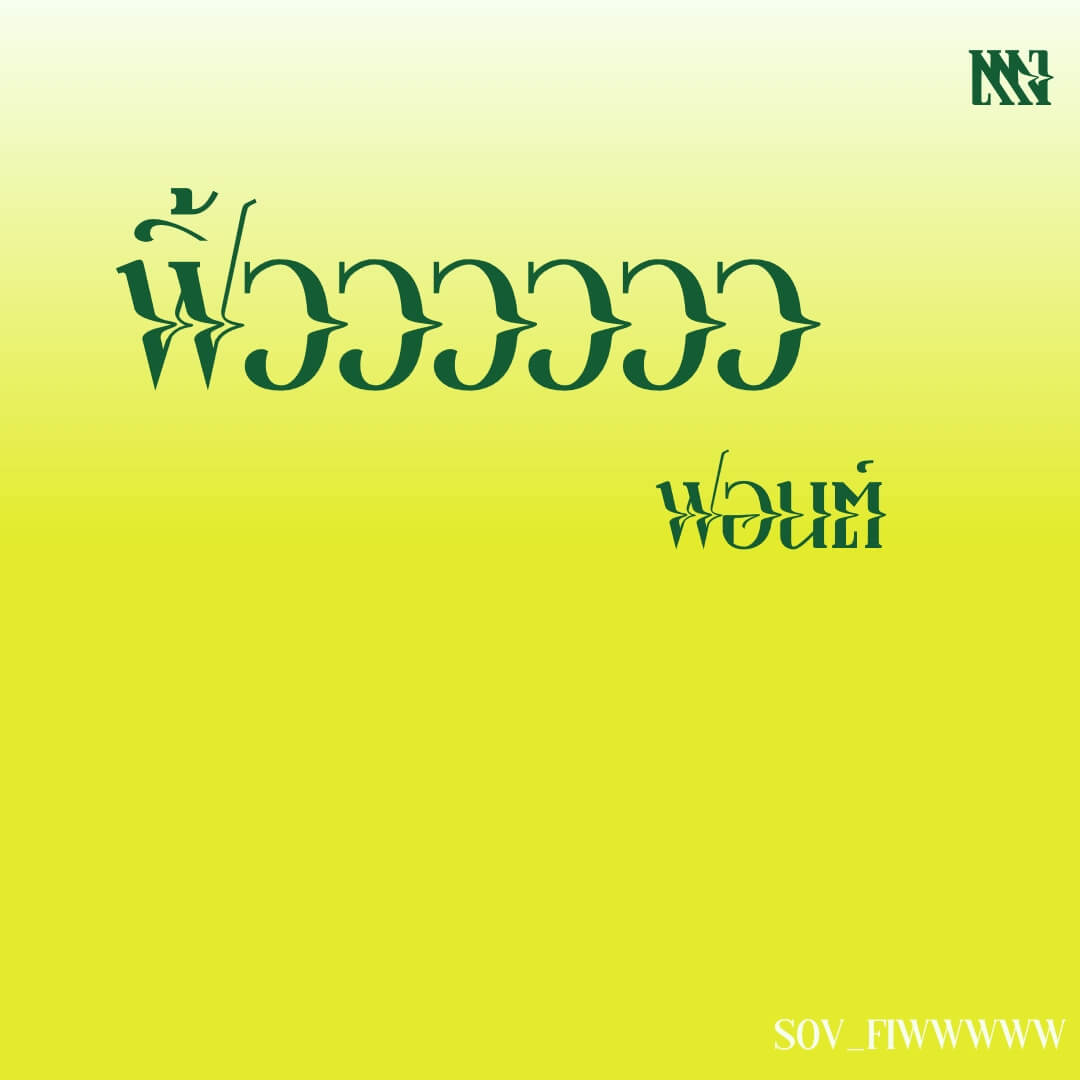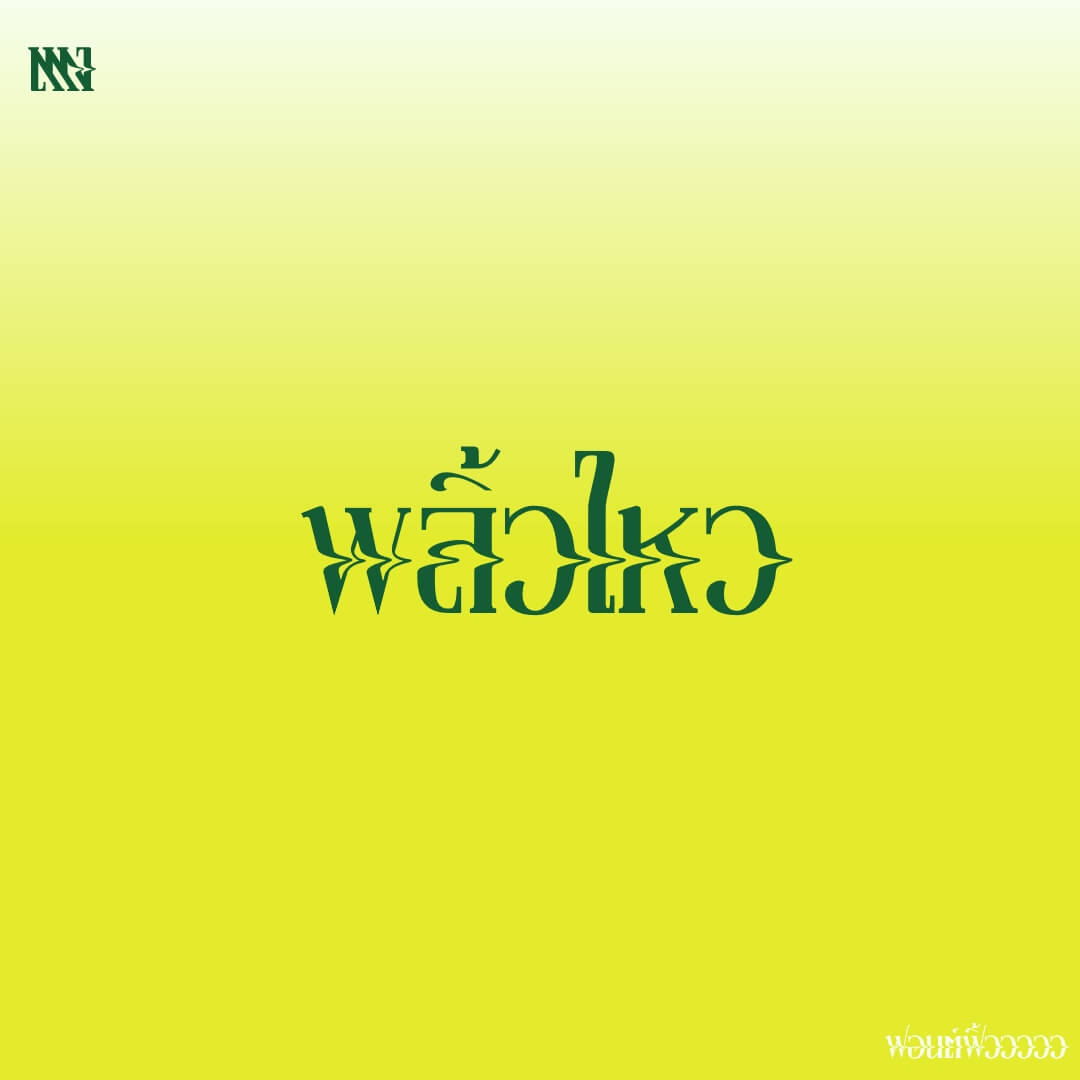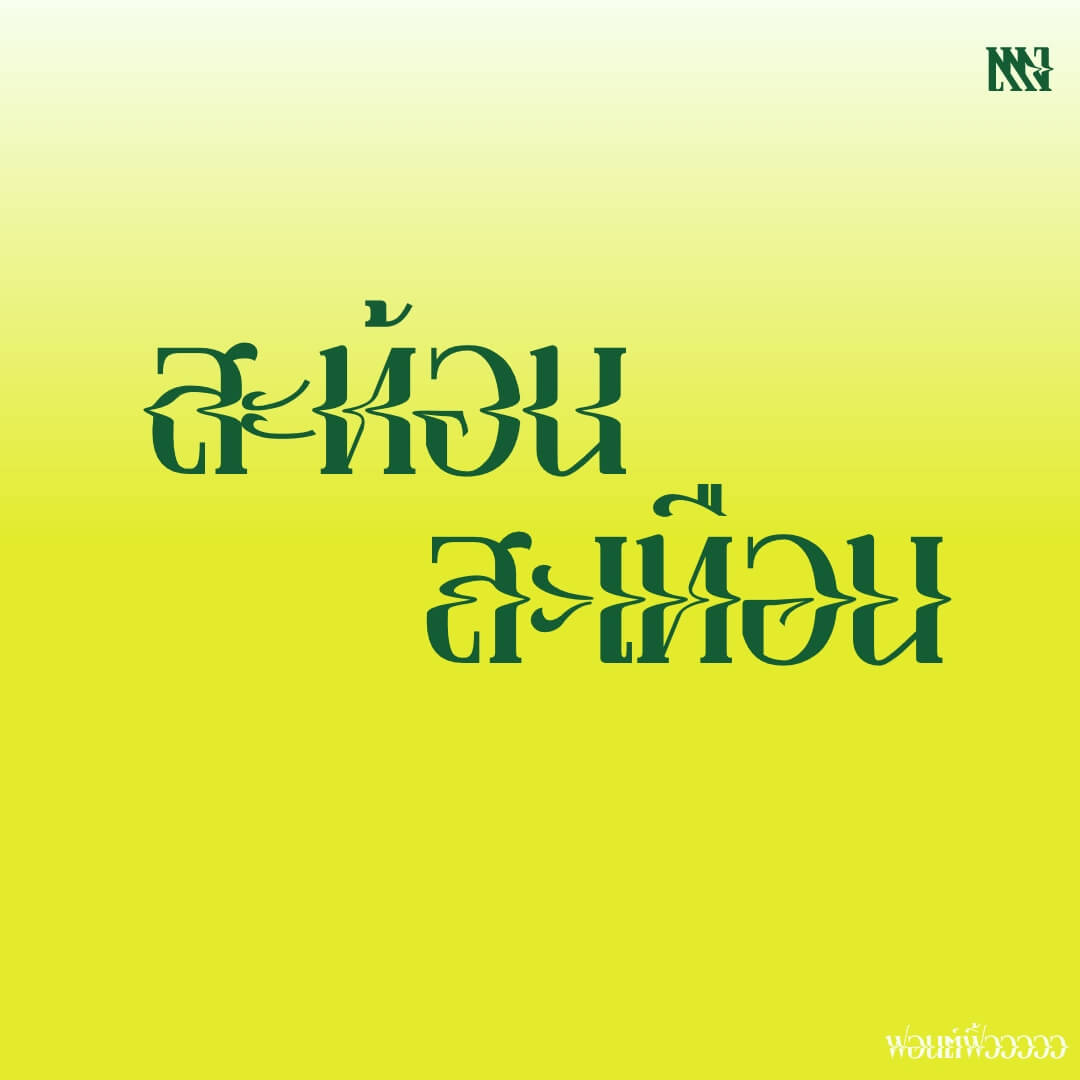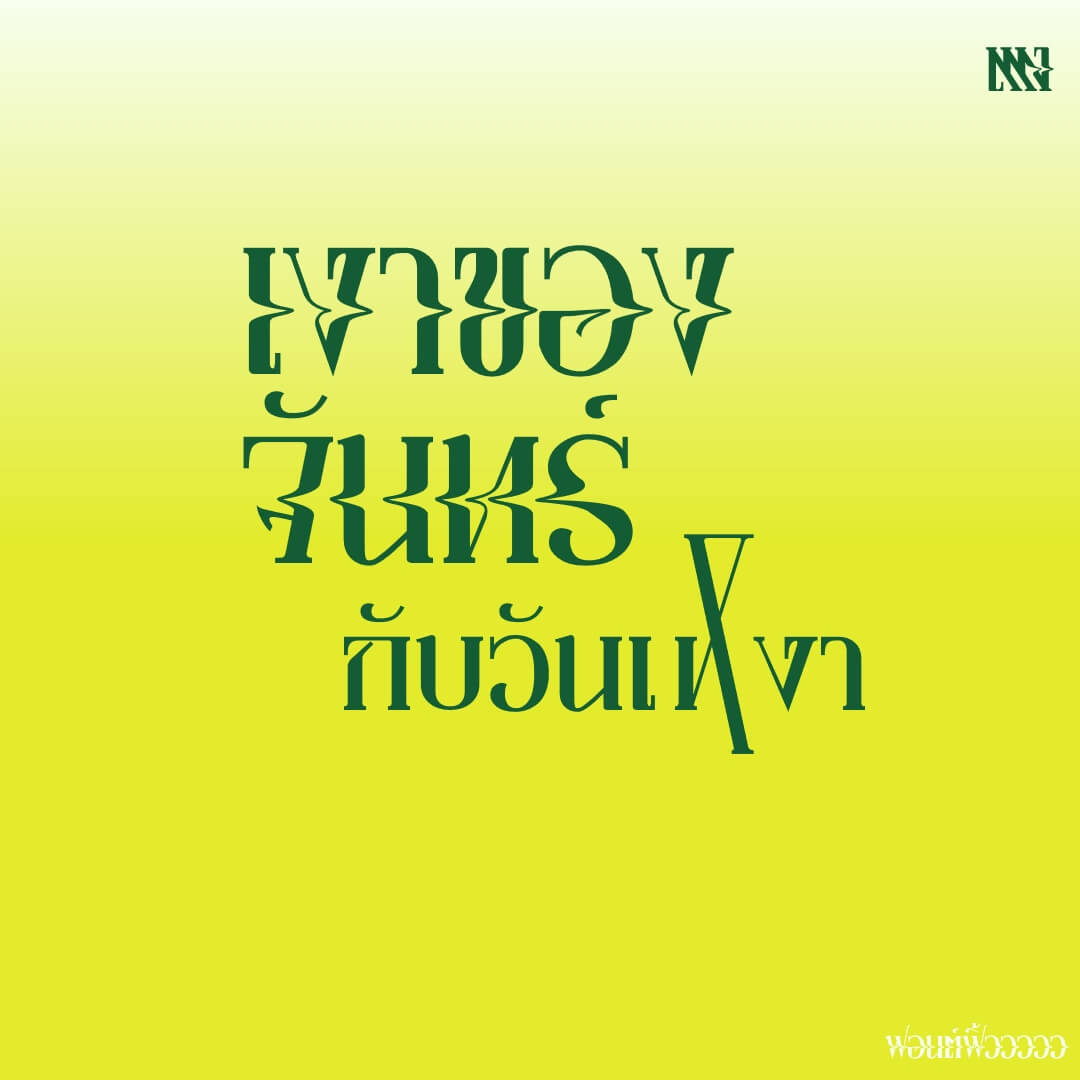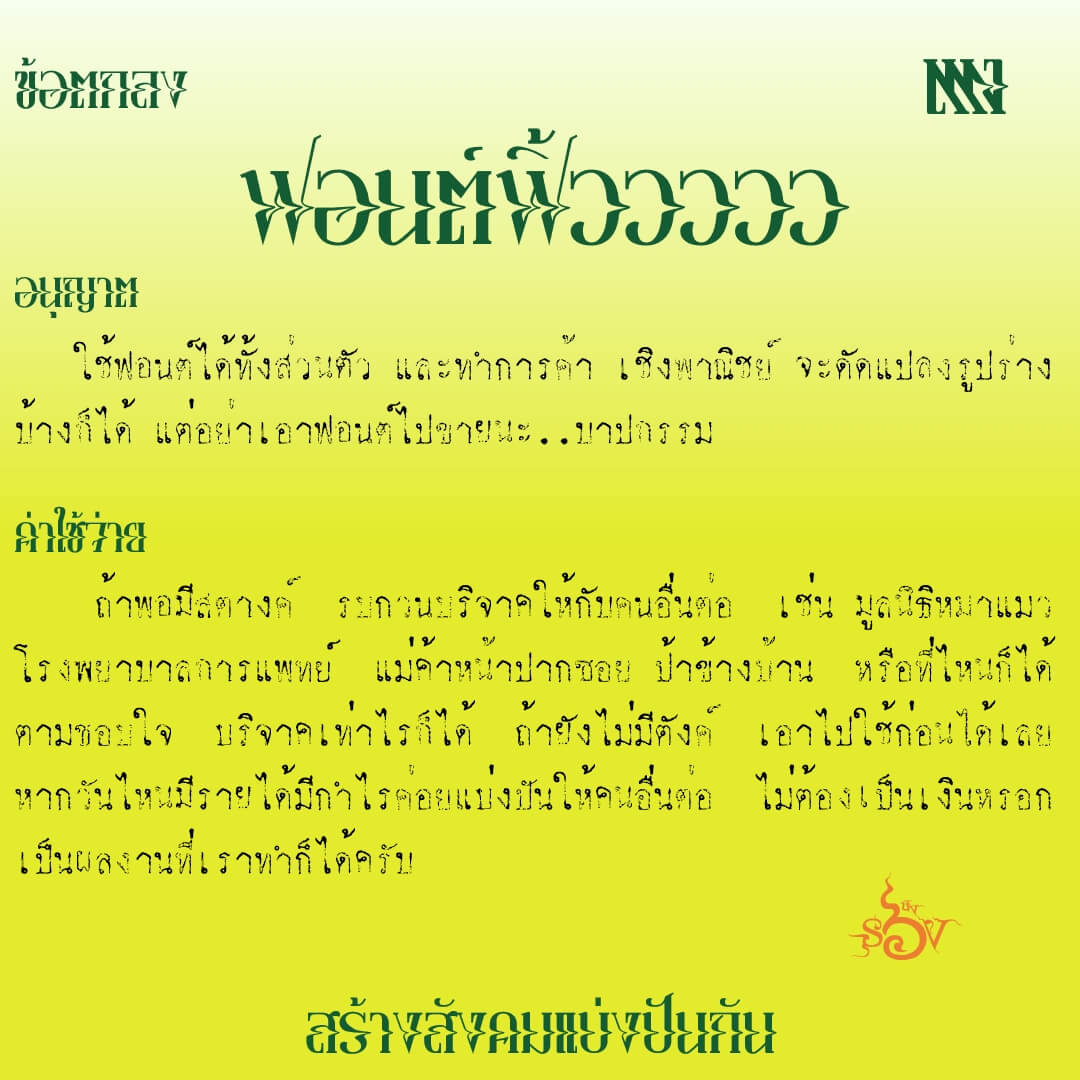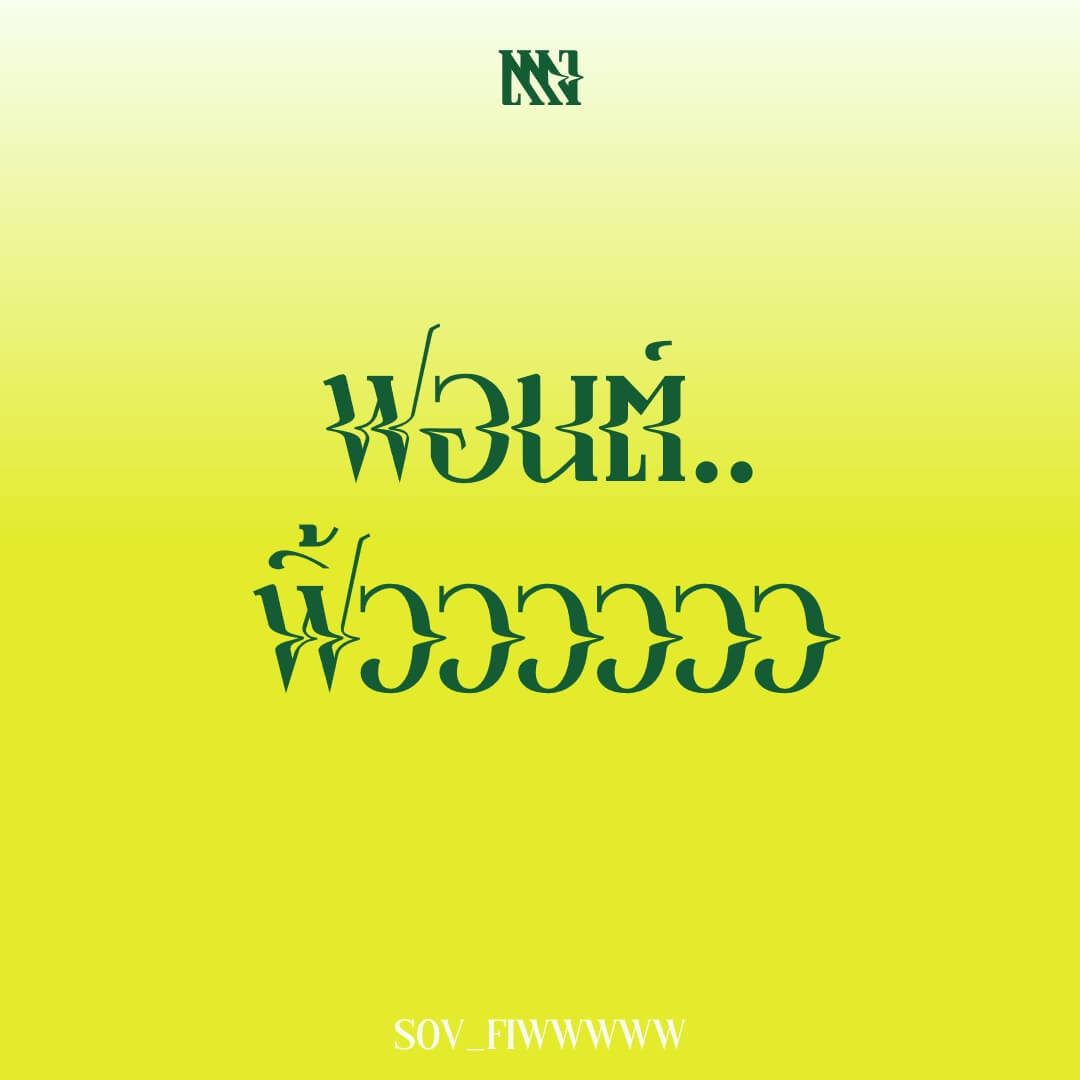
ฟอนต์ ฟิ้ววววว – ฟอนต์ตัวนี้ให้นึกภาพว่า เอาแปรงทาสีร่างตัวอักษรเสร็จ แล้วเอากิ่งไม้เล็กๆ ลากขวาง… ฟิ้ววววว (ตัวปรกติฟิ้วววววไปขวา ตัวหนาฟิ้วววววไปซ้าย)
เบื้องหลังการออกแบบ : ฟอนต์ ฟิ้ววววว
ฟิ้ววววว (SOV_Fiwwwww)